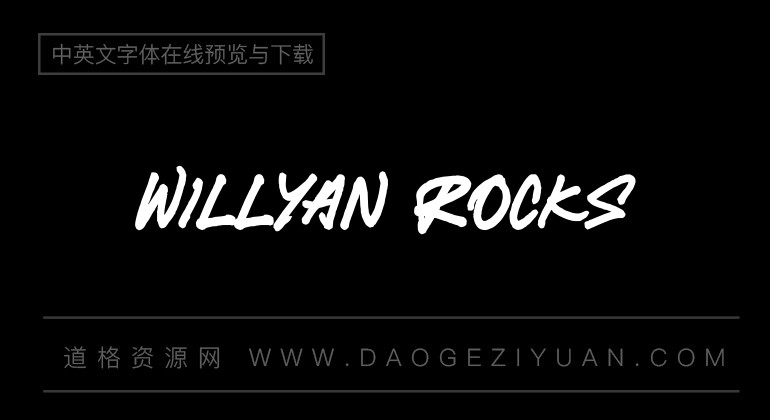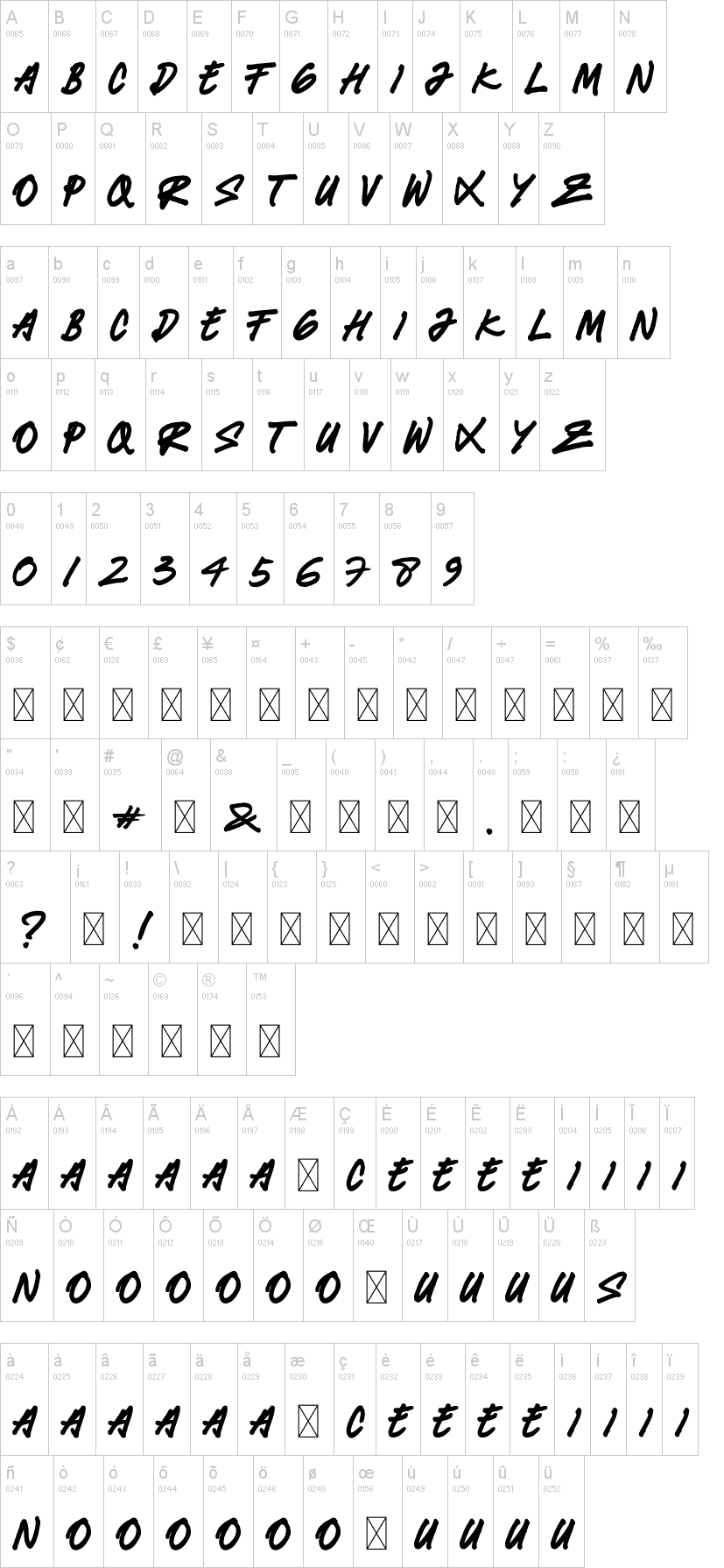
Willyan Rocks 是一款由 Willyan 创作的自由开源字体,它是一款简洁、现代化的英文字体,适用于品牌标志、标题、标签等。它具有清晰的轮廓,可以让您的文本保持简单而有趣的样式。Willyan Rocks 字体有两种字重,分别是 Regular 和 Bold,可以满足您的不同设计需求。内容介绍
Willyan Rocks是一款非常不错的手写艺术字体,具有很好的视觉感,适合于文化类的宣传设计、商业类品牌的广告和产品包装设计以及个性化文字排版等较多场景。